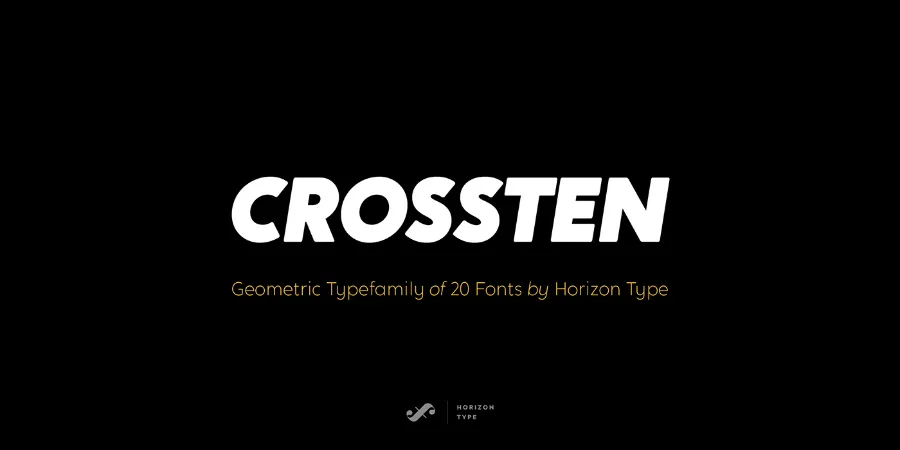
Descubra a riqueza e diversidade do Crossten Font Family em sua página de download. Esta familia grande de 20 fonts é perfeita para qualquer projeto de design, criativo ou não. Feito pela Horizon Type, esta familia de tipo curvilíneo sem serif está baseada em formas geométricas. Crossten oferece um vasto leque de opções: uma coleção completa de 10 estilos de tipo rectos e seus correspondentes itálicos. Em cada peso da fonte há suporte linguístico ampliado. O Crossten é incrivelmente útil para praticamente qualquer tipo de design criativo. Se você está procurando por um conjunto de fonts que possa atender a uma variedade imensa de necessidades, o Crossten Font Family é sua escolha perfeita. Seja para revistas, sites, logotipos ou até mesmo em materiais impressos, ele certamente não decepcionará. Junte-se ao nosso design e faça sua marca brilhar com a fonte ideal do Crossten Font Family.